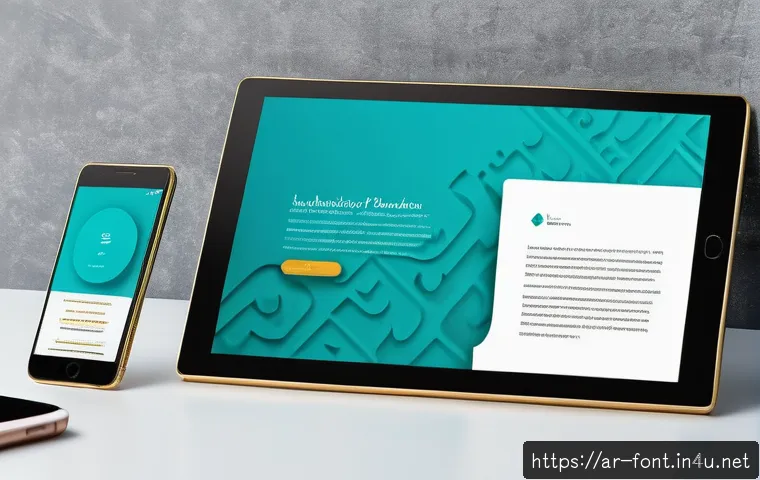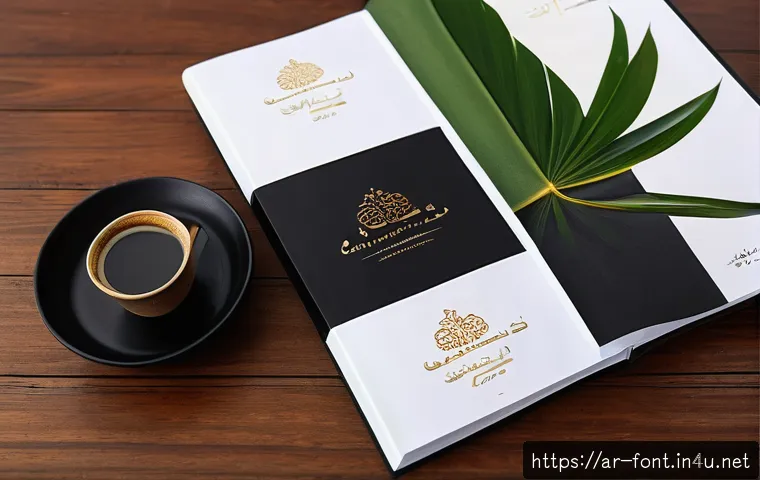
أفضل قوالب وثائق الشركات ودليل الخطوط لتعزيز هوية علامتك التجارية بشكل احترافي
في عالم الأعمال المتغير بسرعة اليوم، أصبحت هوية العلامة التجارية القوية من أهم عوامل النجاح والتفرد في السوق. مع تزايد المنافسة الرقمية، بات اختيار القوالب المناسبة لوثائق الشركات ودليل الخطوط الاحترافي أمرًا لا غنى عنه لتعزيز صورة شركتك وجذب العملاء بثقة.
في هذا المقال، سنكشف لك أسرار اختيار أفضل التصاميم التي تعكس روح علامتك التجارية وتساعدك على التميز بأسلوب أنيق ومنظم. سواء كنت تبدأ مشروعًا جديدًا أو تسعى لتحديث هويتك البصرية، ستجد هنا نصائح قيمة تم تجربتها على أرض الواقع.
تابع معنا لتتعرف على أحدث الاتجاهات التي ستجعل علامتك تترك بصمة لا تُنسى في أذهان جمهورك.
اختيار تصميمات الوثائق التي تعبر عن هوية شركتك بوضوح
تحديد شخصية العلامة التجارية قبل التصميم
قبل أن تبدأ في اختيار أي قالب وثيقة أو دليل خطوط، من الضروري أن تفهم بدقة شخصية علامتك التجارية. هل هي رسمية وجدية؟ أم مرحة ومبتكرة؟ هذا الفهم سيقودك لاختيار الألوان، الخطوط، وأنماط التصميم التي تناسب روح شركتك.
مثلاً، إذا كنت تعمل في مجال التكنولوجيا الحديثة، فقد تفضل الخطوط العصرية والألوان الحيوية التي تعكس الابتكار، بينما الشركات القانونية قد تميل لتصاميم كلاسيكية وألوان هادئة.
تجربتي الشخصية أكدت لي أن قضاء وقت في هذه المرحلة يمنحك نتائج مبهرة تعكس الصورة التي تريدها بدقة.
تناسق الألوان وتأثيرها على الانطباع الأول
الألوان تلعب دورًا حيويًا في تشكيل انطباع العميل عند رؤية وثائقك. من خلال تجربتي، لاحظت أن الألوان المتناسقة تعزز الاحترافية وتجعل الوثائق أكثر جاذبية وأسهل في القراءة.
اختيار لوحة ألوان محدودة (3-4 ألوان كحد أقصى) يمنح تصميمك توازنًا بصريًا مريحًا. أيضًا، يجب أن تتأكد من أن الألوان المختارة تناسب مختلف الوسائط؛ الورقية والإلكترونية.
الألوان الداكنة قد تكون رائعة للطباعات الرسمية، بينما الألوان الفاتحة قد تناسب العروض التقديمية الإلكترونية.
أهمية البساطة في تصميم القوالب
في كثير من الأحيان، البساطة هي مفتاح النجاح. قوالب الوثائق التي تحتوي على تصميمات معقدة قد تشتت الانتباه عن المحتوى الأساسي. من خلال تجربتي مع عدة شركات، وجدت أن القوالب التي تعتمد على خطوط واضحة ومساحات بيضاء كافية تجعل المعلومات أسهل في الفهم وأكثر جذبًا.
لا تخف من استخدام الفراغات بشكل استراتيجي لتجنب الازدحام البصري، فهذا يعكس احترافية ويزيد من وضوح الرسالة.
دليل اختيار الخطوط المناسبة لتعزيز الهوية البصرية
تأثير الخطوط على القارئ وسهولة القراءة
الخطوط ليست مجرد حروف، بل هي أداة تعبير بحد ذاتها. الخط الذي تختاره يؤثر بشكل مباشر على تجربة القارئ ويحدد مدى سهولة استيعاب المحتوى. بناءً على تجربتي، الخطوط التي تتميز بوضوح الحروف ومساحات متساوية بين الكلمات تجعل القراءة مريحة، خصوصًا في الوثائق الرسمية والتقارير.
الخطوط المزخرفة قد تكون مناسبة للعناوين أو الشعارات، لكنها لا تصلح للنصوص الطويلة.
التوازن بين الخطوط الكلاسيكية والحديثة
من الأفضل دمج نوعين من الخطوط: واحد للعناوين وآخر للنصوص الأساسية. على سبيل المثال، استخدام خط عصري وعريض للعناوين يلفت الانتباه، مع خط بسيط وواضح للنصوص يضمن سهولة القراءة.
هذا التوازن يعطي مظهرًا متناسقًا يعكس الاحترافية والحداثة في آن واحد. جربت هذا الأسلوب في شركتي ووجدت أنه يزيد من تفاعل القراء مع المستندات.
حجم الخط والمسافات بين الأسطر
لا تستهين بأهمية حجم الخط والمسافات بين الأسطر، فهي تلعب دورًا كبيرًا في تحسين تجربة القارئ. حجم الخط المناسب يختلف حسب نوع الوثيقة، لكن بشكل عام، الخطوط بين 11 و14 نقطة تعتبر مثالية للنصوص.
كما أن زيادة المسافات بين الأسطر بنسبة معتدلة تمنح النص تهوية بصرية وتساعد على عدم إجهاد العين أثناء القراءة. تأكد دائمًا من اختبار التصميم على شاشات وأجهزة مختلفة لضمان وضوح الخطوط.
كيف تختار قالب وثيقة يعزز مصداقية شركتك؟
التصميم المهني يعكس جدية العمل
أحد أهم الأشياء التي تعلمتها هو أن قالب الوثيقة يعكس مباشرة مدى احترافية شركتك. قالب بسيط، مرتب ومنظم يخلق انطباعًا قويًا بأن شركتك تهتم بالتفاصيل وتقدر عملاءها.
بينما القوالب العشوائية أو غير المتناسقة قد تؤدي إلى فقدان الثقة. لذلك، من الضروري اختيار قالب يعكس قيم شركتك بشكل واضح ويضمن سهولة الوصول للمعلومات.
تخصيص القوالب لتلائم كل قسم في الشركة
ليس من الضروري أن يكون لديك قالب واحد فقط لكل الوثائق. من الأفضل تخصيص قوالب مختلفة تناسب طبيعة كل قسم داخل الشركة، مثل التسويق، الموارد البشرية، والتقنية.
كل قسم له احتياجاته الخاصة من حيث عرض المعلومات وتنسيقها. من خلال تجربتي، تخصيص القوالب يجعل العمل أكثر سلاسة ويعزز من هوية الشركة بشكل متكامل.
المرونة في التعديل والتحديث
اختيار قالب وثيقة يسمح بسهولة التعديل والتحديث أمر ضروري في عالم الأعمال المتغير. قالب ثابت لا يمكن تعديله بسرعة قد يعيق سير العمل أو يجعل الوثائق تبدو قديمة.
القوالب المرنة التي تدعم التحديثات السريعة، خاصة مع التغيرات في الهوية البصرية أو البيانات، توفر وقتًا وجهدًا كبيرين على المدى الطويل.
تأثير دليل الخطوط الموحد على التناسق البصري
أهمية وجود دليل خطوط موحد
دليل الخطوط الموحد هو بمثابة خارطة طريق لكل من يعمل على إنتاج محتوى بصري لشركتك. من تجربتي، وجود دليل واضح يضمن أن جميع المستندات والتصاميم تستخدم نفس الخطوط وبنفس الأسلوب، ما يعزز من هوية الشركة ويجعلها أكثر تميزًا.
بدونه، قد تظهر اختلافات غير مرغوبة تسبب تشويشًا في العلامة التجارية.
كيفية إعداد دليل خطوط فعّال
إعداد دليل خطوط يتطلب تحديد أنواع الخطوط المستخدمة (رئيسية وثانوية)، أحجامها، أوزانها (عادي، عريض، مائل)، والألوان المناسبة. كذلك يجب تضمين أمثلة واضحة على كيفية استخدام الخطوط في العناوين، الفقرات، والعناصر البصرية المختلفة.
بناءً على تجربتي، كلما كان الدليل أكثر تفصيلاً ووضوحًا، كلما زادت سهولة تطبيقه من قبل فريق التصميم أو الموظفين.
تأثير التناسق في الخطوط على ثقة العملاء
عندما يلاحظ العميل تناسقًا في الخطوط والألوان في جميع وثائق الشركة، يشعر بمصداقية أعلى ويعطي انطباعًا بأن الشركة منظمة وتهتم بجودة التفاصيل. هذا بدوره يعزز العلاقة بين الشركة والعملاء ويزيد من فرص التعاون المستقبلي.
التناسق في التفاصيل البسيطة مثل الخطوط له تأثير نفسي كبير على بناء الثقة.
Advertisement
التصميم الرقمي والتكيف مع الأجهزة المختلفة
تحديات تصميم الوثائق الرقمية
تصميم وثائق تناسب العرض الرقمي يختلف عن التصميم الورقي، خصوصًا مع تعدد الأجهزة والشاشات. من تجربتي، يجب أن تكون القوالب مرنة وقابلة للتكيف مع أحجام الشاشات المختلفة سواء كانت هواتف ذكية، أجهزة لوحية أو شاشات كمبيوتر كبيرة.
عدم الاهتمام بهذا الجانب قد يؤدي إلى فقدان جزء كبير من الجمهور أو تقديم تجربة مستخدم سيئة.
اختيار الخطوط المناسبة للعرض الإلكتروني
الخطوط التي تظهر بشكل واضح على الشاشة تختلف عن تلك التي تظهر مطبوعة. الخطوط الرقمية يجب أن تكون واضحة، بسيطة وسهلة القراءة حتى على الشاشات الصغيرة. جربت عدة خطوط في شركتي، ووجدت أن الخطوط التي تدعم تقنيات التنعيم (مثل ClearType) تعطي نتائج ممتازة في العرض الرقمي، خصوصًا عند النصوص الطويلة.
استخدام القوالب الديناميكية والتفاعلية
التطور في تصميم الوثائق الرقمية يسمح الآن باستخدام قوالب تفاعلية تتضمن روابط، أزرار، وعناصر متحركة تعزز تجربة المستخدم. من تجربتي، إدخال هذه العناصر بشكل مدروس لا يشتت القارئ بل يزيد من تفاعله مع المحتوى ويجعل الوثيقة أكثر جذبًا واحترافية.
هذا النوع من القوالب مناسب جدًا للعروض التقديمية والمواد التسويقية الرقمية.
Advertisement
جدول مقارنة بين خصائص القوالب وأنواع الخطوط
العنصر الخصائص الأساسية الفوائد التحديات
قوالب الوثائق تصميم بسيط ومنظم، قابل للتعديل، ملائم للغرض يعزز الاحترافية، يسهل العمل، يعكس هوية الشركة اختيار غير مناسب قد يشتت الانتباه، قد يكون غير مرن
الخطوط الرئيسية واضحة، سهلة القراءة، متناسقة مع الهوية تحسن تجربة القارئ، تعزز التناسق البصري اختيار خاطئ يعيق القراءة، عدم تناسق مع الخطوط الثانوية
الخطوط الثانوية تستخدم للعناوين أو التمييز، متناسقة مع الخطوط الرئيسية تلفت الانتباه، تضيف تميزًا وجمالية إفراط في الاستخدام قد يشتت القارئ، عدم تناسق في الحجم والألوان
الألوان لوحة محدودة، متناسقة مع الهوية، مناسبة للوسائط تعزز الانطباع الأول، تسهل القراءة ألوان متضاربة تضعف المظهر، صعوبة في التكيف مع جميع الوسائط
Advertisement
ختام المقال
اختيار تصميمات الوثائق بعناية يعكس هوية شركتك ويعزز مصداقيتها أمام العملاء. من خلال الانتباه للتفاصيل مثل الألوان، الخطوط، والتنسيق، يمكنك تقديم صورة احترافية ومتناسقة تعبر عن قيم شركتك. لا تتردد في تجربة وتعديل القوالب حتى تصل لأفضل نتيجة تناسب نشاطك. في النهاية، التصميم الجيد هو استثمار يعود بالنفع على سمعة شركتك وعلاقتها مع العملاء.
Advertisement
معلومات مفيدة يجب معرفتها
1. تأكد من أن تصميم الوثائق يعكس شخصية علامتك التجارية بوضوح، فهذا يزيد من تميزك في السوق.
2. استخدام لوحة ألوان محدودة ومتناسقة يساعد في تحسين الانطباع الأول ويجعل الوثائق أكثر جاذبية.
3. اختر خطوطاً واضحة وسهلة القراءة، مع مراعاة حجم الخط والمسافات بين الأسطر لراحة القارئ.
4. تخصيص القوالب لكل قسم في شركتك يسهل العمل ويعزز الهوية البصرية بشكل متكامل.
5. لا تغفل أهمية التصميم الرقمي القابل للتكيف مع مختلف الأجهزة لتحسين تجربة المستخدم.
Advertisement
ملخص النقاط الأساسية
إن تصميم الوثائق هو عنصر أساسي في بناء هوية شركتك ونجاحها التسويقي. يجب أن يكون التصميم مهنيًا ومرنًا مع توفير دليل خطوط موحد لضمان التناسق. الاهتمام بالتفاصيل الصغيرة مثل اختيار الخطوط والألوان يؤثر بشكل كبير على انطباع العملاء ويعزز الثقة. التكيف مع الوسائط الرقمية وتحديث القوالب باستمرار يضمن بقاء شركتك مواكبة للتطورات ويعزز مكانتها في السوق.
الأسئلة الشائعة (FAQ) 📖
س: كيف أختار قالب وثائق يتناسب مع هوية علامتي التجارية بشكل فعّال؟
ج: اختيار القالب المناسب يبدأ بفهم عميق لهوية علامتك التجارية من حيث الألوان، الخطوط، والأسلوب العام الذي يعكس شخصيتها. أنصحك بأن تختار قوالب تبرز تميزك وتتناسب مع طبيعة نشاطك، فمثلاً إذا كانت علامتك رسمية يجب أن يكون التصميم بسيط وأنيق، أما إذا كانت شبابية فالألوان الزاهية والتصاميم الديناميكية تكون أفضل.
جرب عدة قوالب قبل اتخاذ القرار النهائي ولا تنسى أن تتأكد من سهولة تعديلها لتلائم مستجدات شركتك مستقبلاً.
س: ما أهمية دليل الخطوط في تعزيز هوية العلامة التجارية وكيف يمكنني تصميمه بطريقة احترافية؟
ج: دليل الخطوط هو عنصر أساسي لأنه يضمن توحيد المظهر البصري في جميع مستنداتك، مما يعزز تميّز علامتك ويزيد من احترافية التواصل مع العملاء. بناءً على تجربتي، أنصحك باختيار خطوط واضحة وسهلة القراءة تتناسب مع طبيعة علامتك، وتحديد استخدامات كل خط (مثل العناوين، النصوص العادية، والتعليقات).
كما يجب أن يشمل الدليل تعليمات دقيقة حول حجم الخط، التباعد، والألوان المستخدمة. وجود هذا الدليل يجعل فريق العمل والعملاء يشعرون بالثقة والاتساق في كل تواصل.
س: هل من الضروري تحديث هوية العلامة التجارية بشكل دوري، وما هي العلامات التي تدل على حاجتها للتحديث؟
ج: نعم، تحديث الهوية البصرية ضروري للحفاظ على صلة علامتك بالسوق والعملاء، خاصة مع تغير الاتجاهات والتكنولوجيا. من العلامات التي تشير إلى الحاجة للتحديث: شعور العملاء بأن تصميمك قديم أو غير جذاب، صعوبة في تطبيق الهوية على منصات جديدة، أو توسع نشاطك الذي يتطلب تعبيرًا بصريًا مختلفًا.
بناءً على تجربتي، التحديث لا يعني تغيير كامل بل تحسينات مدروسة تحافظ على جوهر العلامة وتمنحها حيوية جديدة تساعدك في المنافسة بثقة.